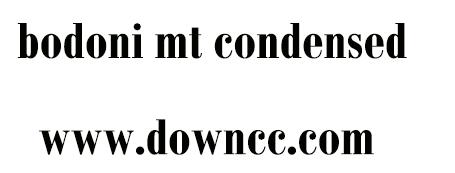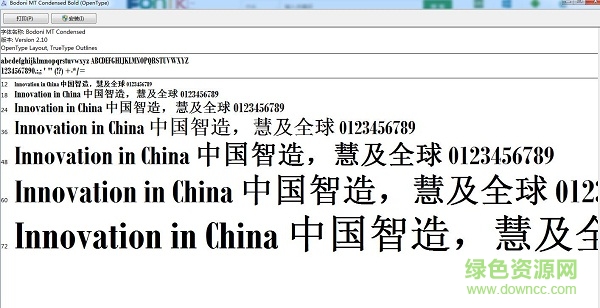
bodoni mt condensed 普通
bodonimtcondensed字體是一款普通襯線字體,字體結(jié)構(gòu)設(shè)計(jì)新穎而不失規(guī)矩,字形優(yōu)美,表現(xiàn)力強(qiáng),用在廣告、雜志、宣傳畫報(bào)等方面非常合適,歡迎需要的小伙伴們前來下載!